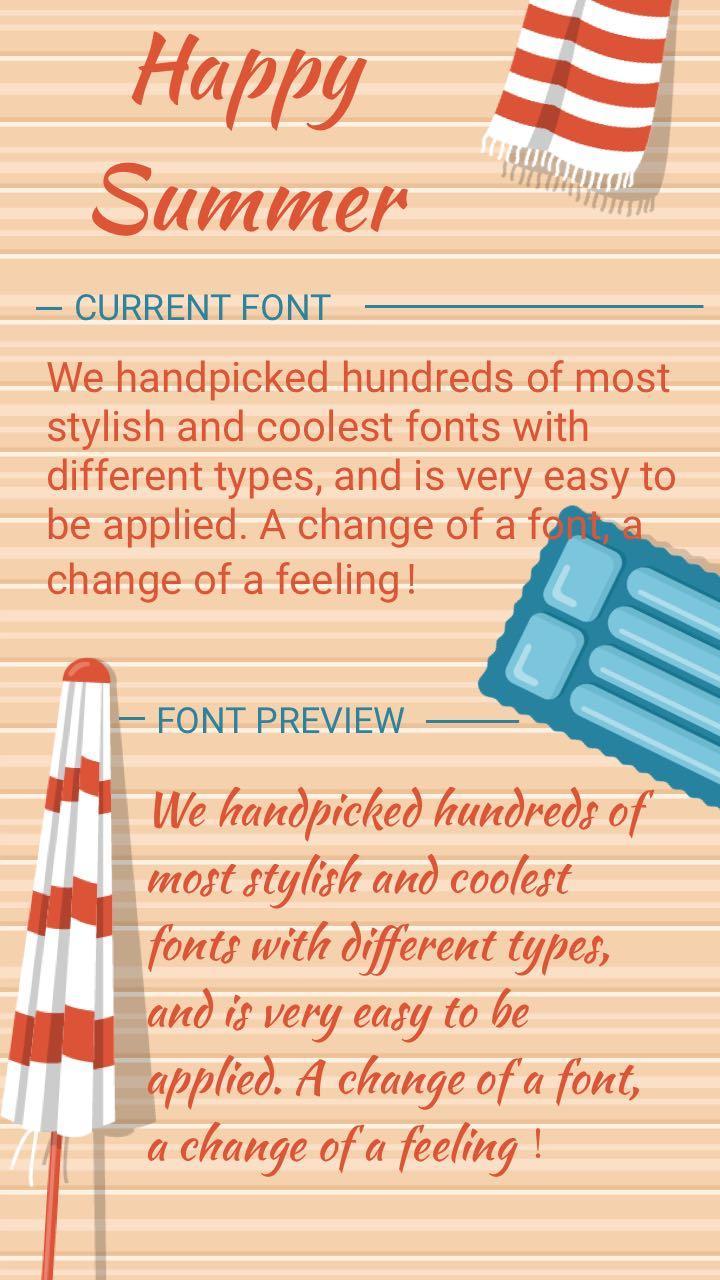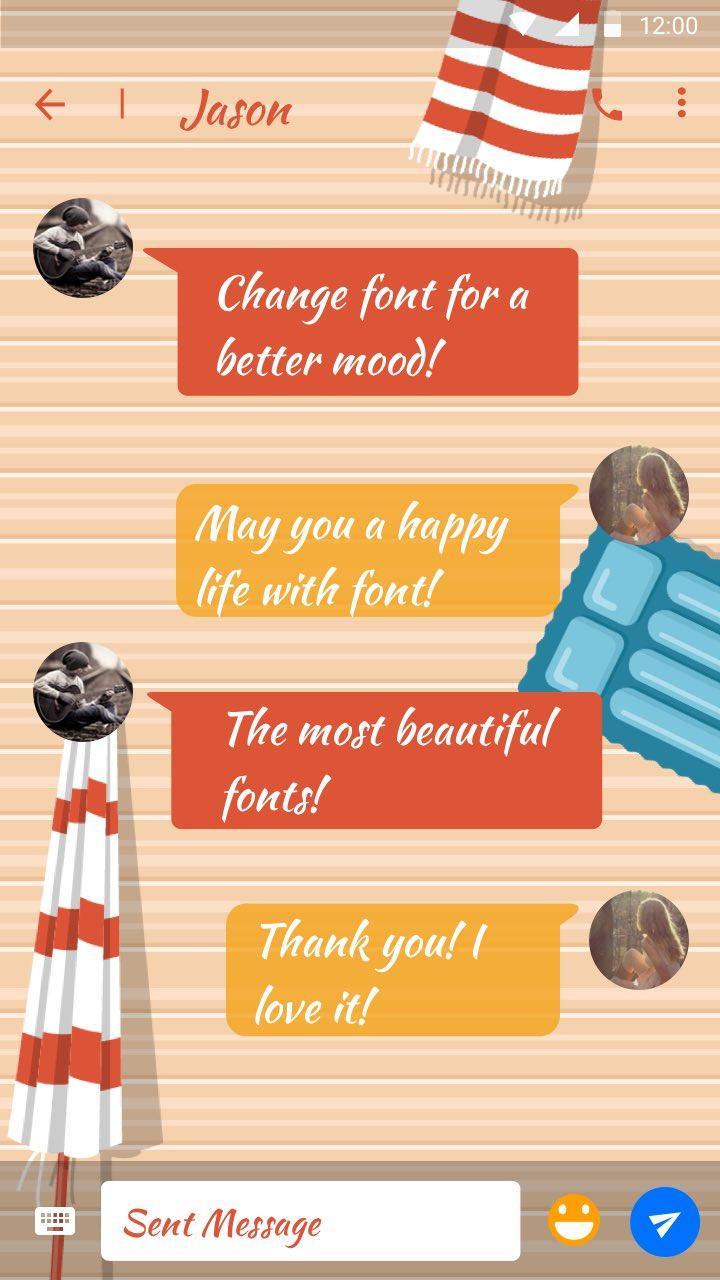
Centenas de fontes selecionadas têm o estilo de fontes manuscritas, como Happy Summer, como fofas, escuras, quadrinhos, galáxia, amor, rosa, sexy, fontes escritas coloridas, fontes limpas, fontes doces, etc. Não espere, basta baixar uma fonte que você gostar mais. E é compatível com o programa de fontes do seu telefone! 👏👏❤❤🌹🌹
Happy Summer